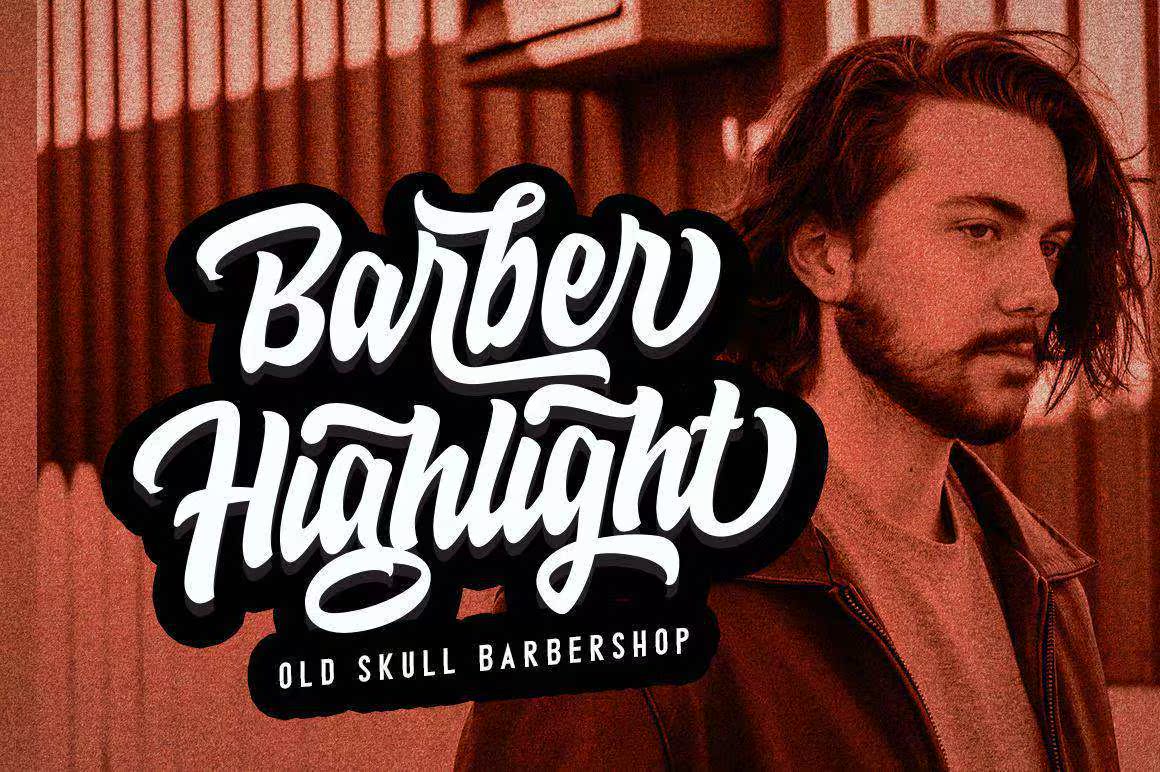
HoodsonScript灵感来源于RetroStyle,并结合了手写风格。我的个人风格会触动每一条曲线。我希望这能让你从工作中获得灵感。每一条漂亮的基线都能完美地画出赞美的MarkerFont,以及完美的BonusWash。理想的徽标、手写报价、产品包装、标题、海报、商品、,社交媒体和问候卡。HoodsonScript灵感来源于RetroStyle,并与手写字体风格相结合。我将个性融入到每一条曲线中。我希望这能让你从工作中获得灵感。每一个BouncyBaselines都有完美的修饰、赞美、标记、以及完美的洗礼。理想的徽标、手写报价、产品包装、标题、,海报、商品、社交媒体和问候卡。